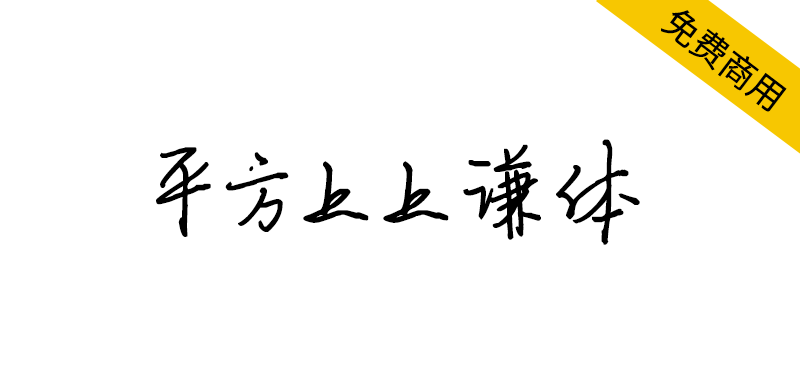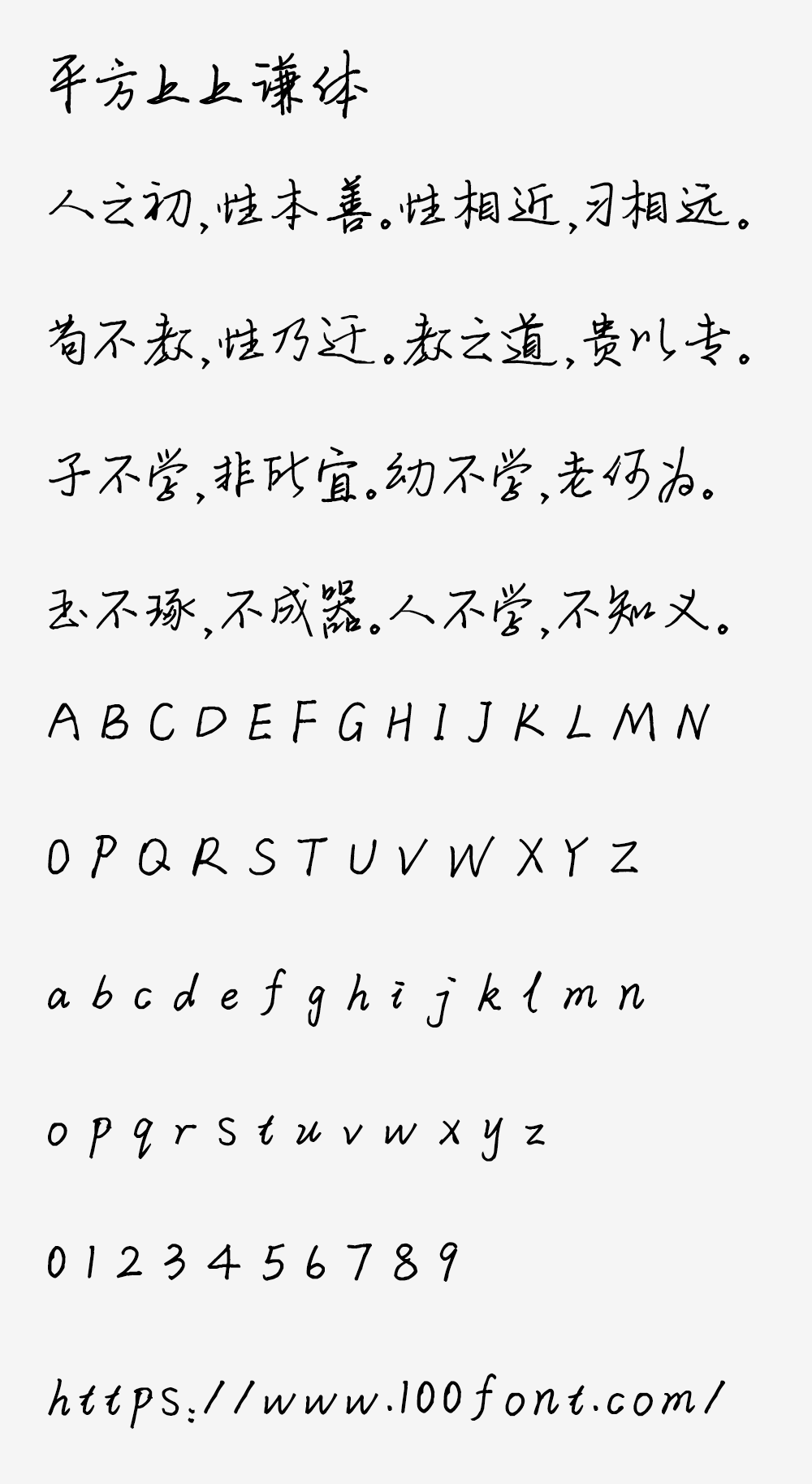
【平方上上谦体】具有洒脱韵味的硬笔书法字体
你是否厌倦了千篇一律的字体?这款“平方上上谦体”悄然走红,以其修长流畅的线条和自然洒脱的硬笔书法韵味,正成为设计新宠。不仅免费商用,还能一键预览效果,适用于广告、电商、自媒体等多元场景。它凭什么脱颖而出?背后又有怎样的使用边界?揭开这款高颜值字体的神秘面纱,让你的排版瞬间提升格调。
【平方上上谦体】具有洒脱韵味的硬笔书法字体
平方上上谦体是一款独具特色的硬笔书法字体,其线条修长流畅,笔势自然连贯,在连笔中透着一份洒脱韵味,优雅大方,可用于各类文字排版与设计需求。